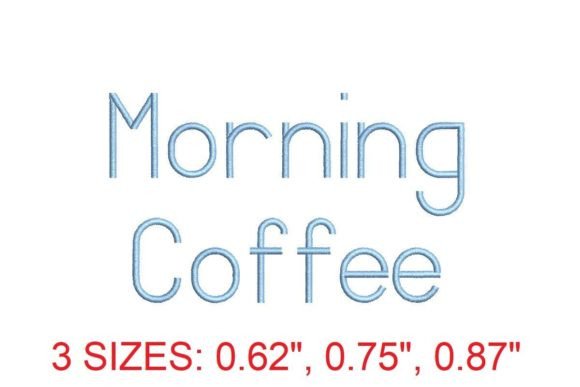
Morning Coffee Embroidery Font
Поиск подходящих элементов дизайна может быть сложным, но Morning Coffee Embroidery Font предлагает исключительную коллекцию, которая мгновенно улучшит вашу работу.
Созданный с высокой точностью, Morning Coffee Embroidery Font предоставляет чистые векторы, плавную типографику и коммерческую лицензию для вашего спокойствия.
Создаете ли вы продукты POD (печать по требованию), свадебные приглашения или графику для социальных сетей, Morning Coffee Embroidery Font станет идеальным выбором.